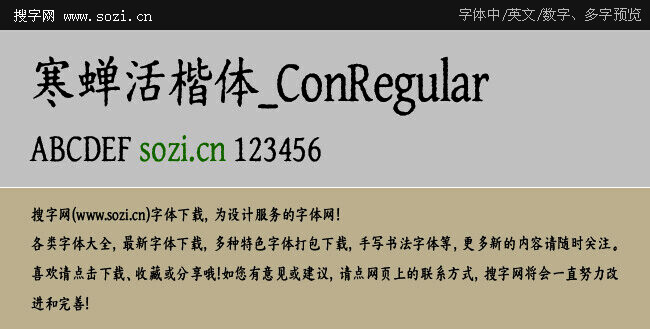
寒蝉活楷体_ConRegular
搜字网提供一款寒蝉活楷体_ConRegular中文书法字体下载,寒蝉活楷体是一款基于寒蝉正楷体修改的复古活字印刷字体,旨在已有的开源字体上修改模拟具有轻度油墨溢出的效果。将清晰的字体变得略微模糊,将顺滑流畅的曲线修改为驳杂的曲线。复古的字形,斑驳的纹理,与原字体对比多了几分真实。这款字体无论是个人还是企业都可以自由免费商用,无需知会或者标明原作者。适合海报设计、广告创意设计等应用。